「喜怒哀楽」の感情表現にぴったりな日本語フリーフォント
今回は「喜怒哀楽」の感情表現ぴったりなおすすめ日本語フリーフォントをまとめてみました。
フォントや文字だけでも「喜怒哀楽」を表現することができます。喜び、怒り、悲しみ、楽しみの4つの感情ごとにフォントをまとめているので、目的にあわせて参考にしてみてください。
デザイン・動画制作・テロップ・漫画セリフなど幅広い場面で活用できるフォントばかりなので、ぜひ揃えておきたいフォントです。
「喜怒哀楽」におすすめのフォントまとめ
以下のように文字からの印象から「喜怒哀楽」の表情が見えることができます。以下サンプル画像は、本記事のフォントの一部ですが、他にもたくさんのフォントを紹介しているので、自分が求めている感情のフォントをぜひ見つけてみてくださいね!
「喜び」におすすめのフォントまとめ
「喜び」におすすめのフォントまとめました。喜んでる雰囲気が表現できるようにリズミカルや動きがあるフォントを選んでいます。
源暎ぽっぷる
源暎ぽっぷるフォントは、手書き風な曲線が可愛いらしいPOP体風仮名のゴシック体フォントです。女子が書いたようなコロコロと丸っこい雰囲気が印象的です。
キルゴUは、人気マンガのタイトルロゴをモチーフに制作されたフォントです。コロコロしていて喜んでいる雰囲気があるフォントです。
けいふぉんと
けいふぉんとは、アニメロゴで使われたロゴタイプに似せているため、リズミカルなフォルムで、同人誌やアニメや動画のサムネイル・アイキャッチなどに取り入れると可愛らしさと喜びが表現できるフォントです。
あかずきんポップ
あかずきんポップフォントは、軽やかで弾むような、喜んでいる雰囲気のあるキュートなPOP体フォントです。
ポプらむ☆キウイ
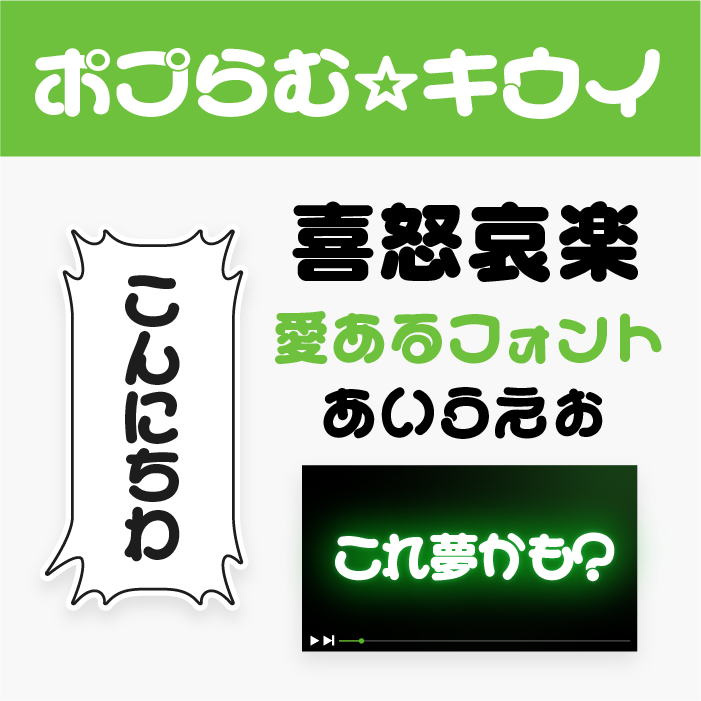
ポプらむ☆キウイフォントは、少女向けマンガなどに使われていそうな丸みがある可愛くポップな文字になっています。
「怒り」におすすめのフォントまとめ
「怒り」におすすめのフォントまとめました。怒っている雰囲気が表現できるように文字が尖っていたり、ビリビリブルブルと震えがあるフォントを選んでいます。
レゲエONE
レゲエOne(Reggae One)フォントは、文字の先端に鋭角に尖っている形状が特徴的なユニークなフォントになります。怒っている文字として、テロップやセリフとして人気のフォントです。
チカラヅヨク
851チカラヅヨクフォントは、ぶっといペンで書いたかのようなペンの字のフォントです。殴り書きしたような怒りの勢いがあるフォントです。
ロックンロール
ロックンロールOne(RocknRoll One)フォントは、文字の先端にかけ先細っているラインの形状をし、点などは丸で形成されているユニークなフォントになります。
吐き溜
吐き溜フォントは、「下町の恐怖フォント」をテーマとして制作されたホラー系フォントです。怒りを通り越した人間味のある怖さを感じるフォントです。
白舟古印
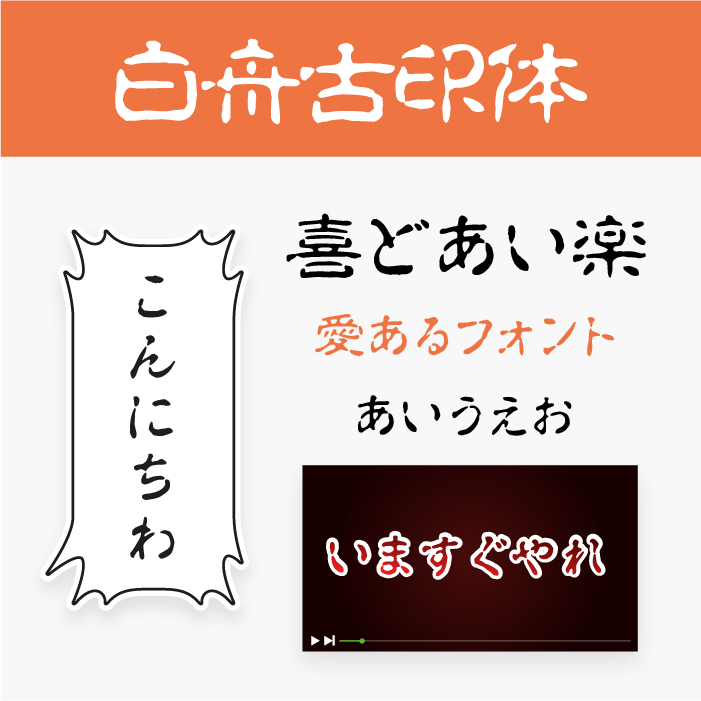
白舟篆古印フォントは、白舟書体の家業だった印章業としてのノウハウがぎゅっと詰まっている古印体をベースに篆書(てんしょ)体の特徴を取り入れたフォントです。
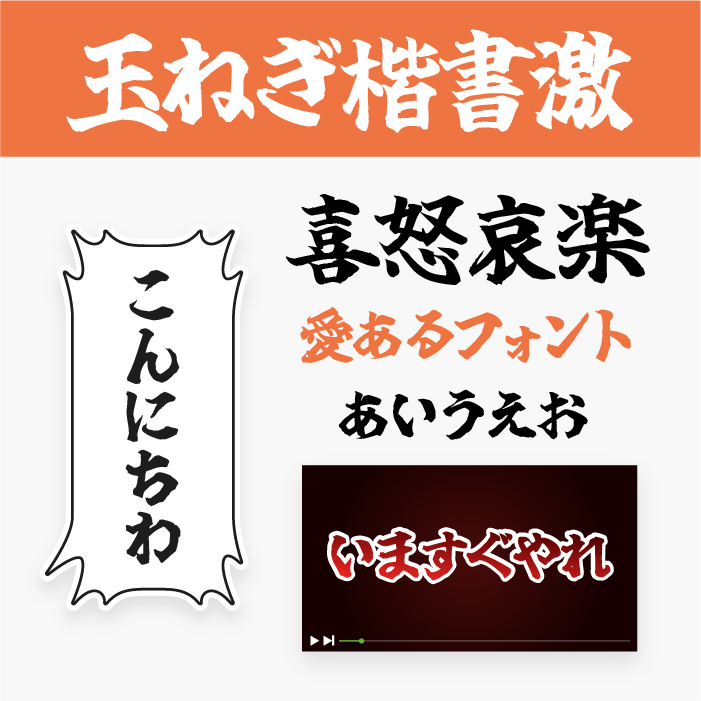
玉ねぎ楷書「激」フォントは、毛筆で力強く書かれた楷書フォントです。力強いハネやハライが大胆でインパクトので、注意などの強く発言する感情などにぴったりです。
「哀しみ(悲しみ)」におすすめのフォントまとめ
「哀しみ(悲しみ)」におすすめのフォントまとめました。哀しみ(悲しみ)の雰囲気が表現できるように文字が泣きが出しそうな切ないフォントを選んでいます。
チカラヨワク
851チカラヨワクフォントは、弱々しくフニャフニャのフリーフォントです。フニャ〜っとした弱々しい様子が表現されているフォントです。
号泣ゴシック
号泣ゴシックフォントは、泣いているような水滴が垂れているユニークなデザインのゴシック体フォントです。哀しみ感が溢れるフォントです。
カットガラスG
カットガラスGフォントは、カットガラスのテクスチャの加工が加えられているデザインフォントです。消えてしまいそうな切ない雰囲気を感じるデザインです。
焔明朝
焔明朝フォントは、今にも消えてしまいそうな炎のようなゆらぎ加工が施されているフォントになっています。
ふぉんとうは怖い明朝体
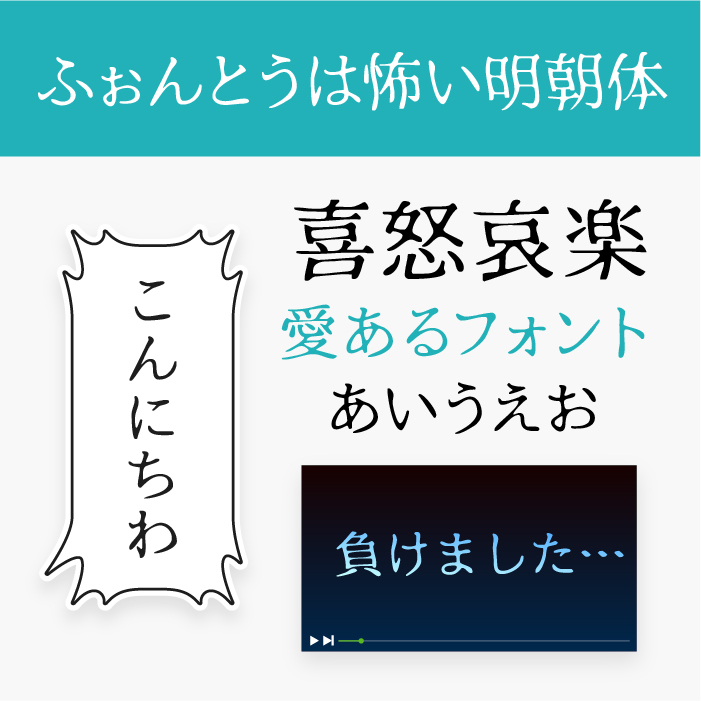
ふぉんとうは怖い明朝体フォントは、文字にグニャーっとゆらぎの加工を施した少し怖い印象があるフォントです。
流怪譚
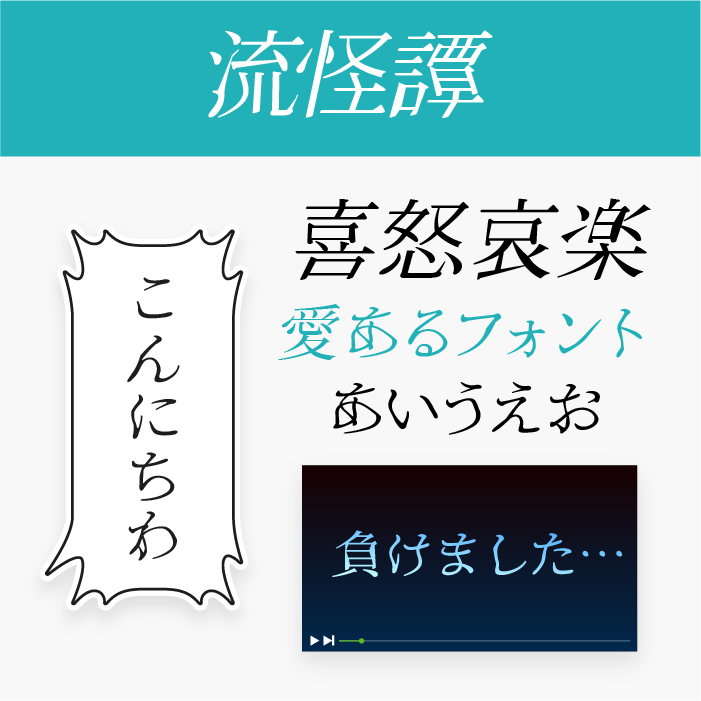
流怪譚フォントは、ゆらゆら揺れているような怪奇的な雰囲気のあるユニークな明朝体フォントです。
コミックホラー恐怖
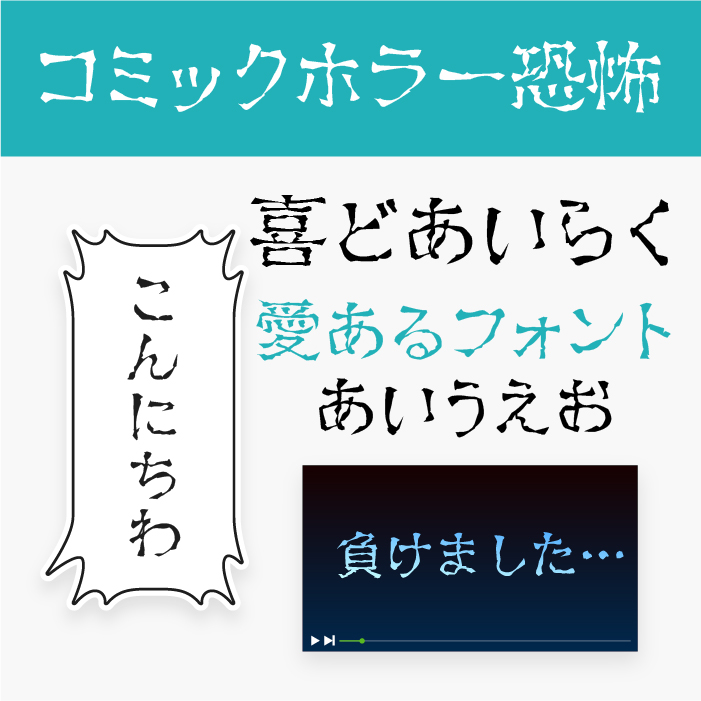
コミックホラー恐怖フォントは、文字にギザギザな加工が施されており、恐怖表現をよくマンガなどに用いられているような文字なので、怖さを倍増させてくれるようなフォントになっています。
「楽しみ」におすすめのフォントまとめ
「楽しみ」におすすめのフォントまとめました。楽しみの雰囲気が表現できるように文字がルンルンとした楽しげで幸せを感じるフォントを選んでいます。
天浜線フォント
天浜線フォントは、静岡県西部のローカル線「天竜浜名湖鉄道(通称:天浜線)」の看板で使われていた手書き文字を静岡大学の学生がフォント化プロジェクトで制作されたフォントです。
手書き感のある文字が楽しさを感じさせます。
にくまる
にくまるフォントは、ゆるくて、てきとうな、柔らかい雰囲気が特徴のフォントです。まるまるっと太ったフォルムは愛らしく可愛らしいデザインになっています。
解星オプティ
解星オプティ(Kaisei Opti)フォントは、文字先に付いているドットの丸い装飾が可愛らしさとルンルンと楽しい雰囲気を感じるフォントです。
くるる源
GL-くるる源フォントは、文字に細かい渦巻きが入っているオリジナルのひらがな・カタカナ文字に源ノ明朝を混植されたデザインフォントです。
源暎きわみゴ
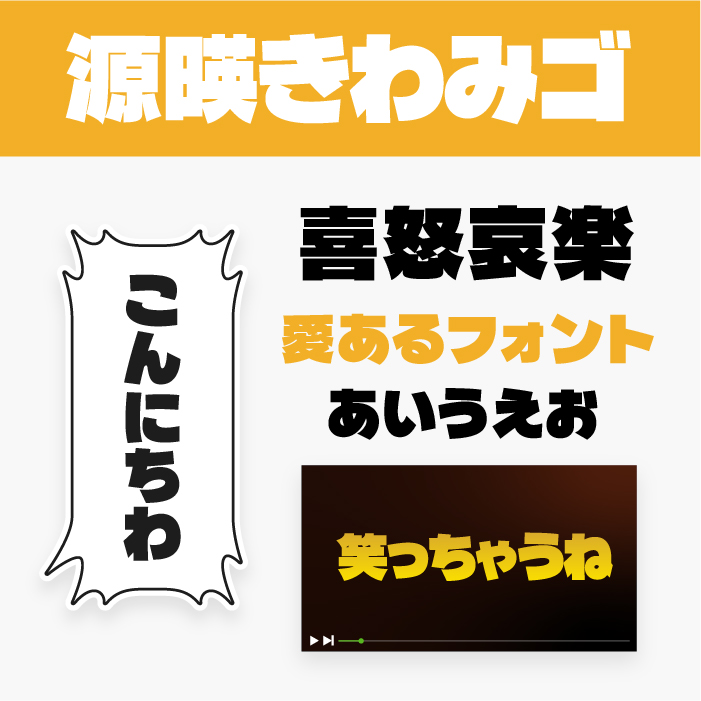
源暎きわみゴフォントは、ドドンとインパクトがあり強い印象があり、目を引くフォントでコミカルで楽しそうな雰囲気のあるので、サムネイルやテロップなどにさまざまな場面で活躍できるフォントです。